Tipografía inclusiva de género: ¿Economizar el lenguaje y ser inclusivo es posible?
Desde que se inventó la escritura, los humanos hemos buscado la forma de simplificarla al máximo, creando sistemas universales con caracteres fácilmente reconocibles y agilizando así tanto el proceso de escritura como de lectura, hasta llegar a la actualidad. Como sabéis, en Crece Agency somos unos apasionados de las tipografías experimentales y rompedoras. Tras una interesante investigación, dimos con una corriente tipográfica vanguardista y hasta el momento no explorada en nuestro país (ni en nuestro idioma): la tipografía inclusiva de género.
El lenguaje inclusivo ha sido un tema de controversia durante los últimos años. En varias ocasiones hemos podido ver a la RAE posicionarse en contra de las expresiones de lenguaje inclusivo que han surgido con el tiempo y cuyo uso sigue extendiéndose. Nos referimos al uso de la “@”, la “x” y la “e” para los plurales neutros.
Al parecer, la RAE lo tiene bien claro: «se considera innecesaria la inclusión del doble género, es decir, “todos y todas”, así como el uso del llamado “lenguaje inclusivo” que utiliza “x”, “@” o “e” en lugar del plural, es decir, “todxs”, “tod@s” o “todes”».
A pesar de haber manifestado su opinión en varias ocasiones, poco es el caso que los internautas han hecho de las declaraciones de la Real Academia de la Lengua Española, y poco es el caso que le vamos a hacer nosotrxs también.
La necesidad de crear lenguajes inclusivos, libres de género, en ciertos idiomas, es cada vez más creciente en una sociedad que lucha por la visibilidad y la igualdad de género. Por este motivo, no es extraño que se hayan empezado a buscar soluciones más allá del enfoque lingüístico. ¿A nadie se le ha ocurrido un enfoque desde el punto de vista tipográfico?
Lo cierto es que sí. Un estudiante suizo llamado Tristan Bartolini ha diseñado una tipografía con más de 40 símbolos nuevos en favor de una escritura sin género, proyecto por el cual ha sido galardonado con el Prix Art Humanité de la Cruz Roja de Ginebra, un premio que da reconocimiento a ideas que combinan espíritu artístico y compromiso humanitario. Esta tipografía experimental aporta una solución gráfica al problema de la dualidad de género en la gramática francesa mediante la combinación de dos o más letras en un mismo carácter.
Desde Crece Agency hemos querido aportar nuestro granito de arena a la búsqueda de un sistema de escritura sin género. Inspirándose en el proyecto de Bartolini, “L’inclusif-ve”, nuestro diseñador Ciscu Gómez ha ideado nuestra propia versión de una tipografía inclusiva de género en lengua española. Mientras que Tristan aportó su visión desde la rama artística, nosotros hemos basado el diseño de estos nuevos caracteres en un sistema de ligaduras para facilitar al máximo su legibilidad y economizar su escritura. En otras palabras, hemos supeditado la estética a la funcionalidad de los nuevos símbolos. La muestra tipográfica que hemos usado es la Museo Font de Exljbris Font Foundry, una tipografía sencilla, de fácil legibilidad pero con acabados en forma de serifa muy originales que la hacen única.
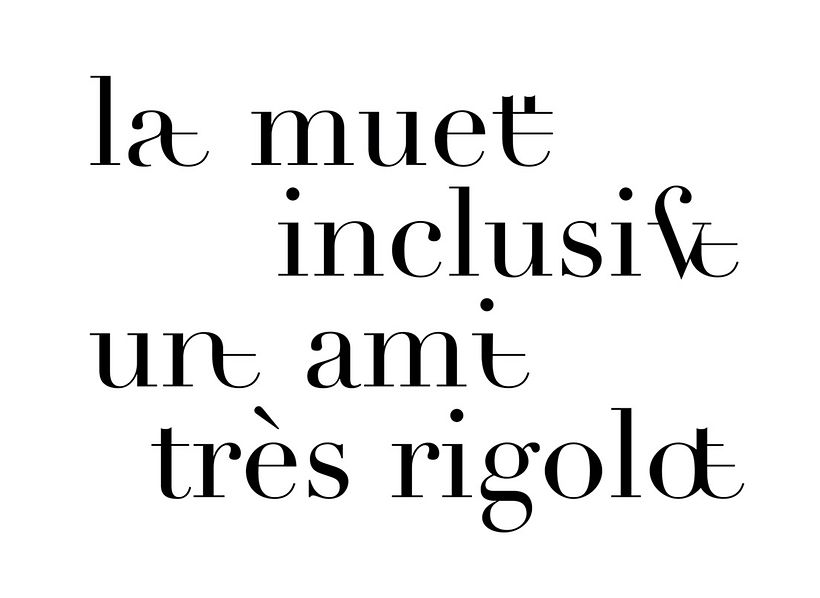
Siguiendo esta línea de diseño, hemos ideado tres símbolos nuevos que responden a tres necesidades de inclusión de género que consideramos fundamentales en la lengua española: el carácter “el/la”, el carácter “a/o” y el carácter “p/m”. Los tres símbolos buscan aunar el género masculino con el femenino de manera que se economice el lenguaje pero sin invisibilizar el género femenino, como en ocasiones ocurre cuando decimos “los padres”, cuando realmente nos estamos refiriendo a “el padre y la madre” o incluso a “las madres”.
El castellano es una lengua con una fuerte carga de género. Para los diseñadores es todo un reto tratar de aportar soluciones gráficas inclusivas a la par que estéticamente agradables, tratando de buscar alternativas más funcionales y serias que las usuales “x”, “@” y “e”. Esta es solamente una propuesta que hacemos desde nuestra agencia, una tipografía experimental que intenta dar respuesta a una necesidad gráfica y social cada vez más presente.
No podemos forzar la evolución del alfabeto de la noche a la mañana, ya que, al igual que la evolución de la lengua, es un proceso orgánico que debe darse de manera natural mediante su uso. Un buen ejemplo es el alfabeto Braille, que fue diseñado por un joven ciego, Louis Braille, ante la necesidad de hacer más funcional e intuitivo el sistema de Barbier, que es el que se utilizaba hasta el momento para enseñar a leer a las personas ciegas. El sistema de Barbier era ingenioso, partía de una buena idea: generar un sistema de escritura que permitiera a los soldados y oficiales franceses redactar y leer mensajes encriptados en la oscuridad y poder descifrarlos con los dedos. Sin embargo, Braille supo perfeccionar su diseño y lo hizo accesible y funcional para todo el mundo.
Igual que pasó con el alfabeto Braille, estamos convencidos de que con el tiempo y con la práctica irán surgiendo nuevas propuestas de sistemas de escritura universales, como esta tipografía inclusiva de género.
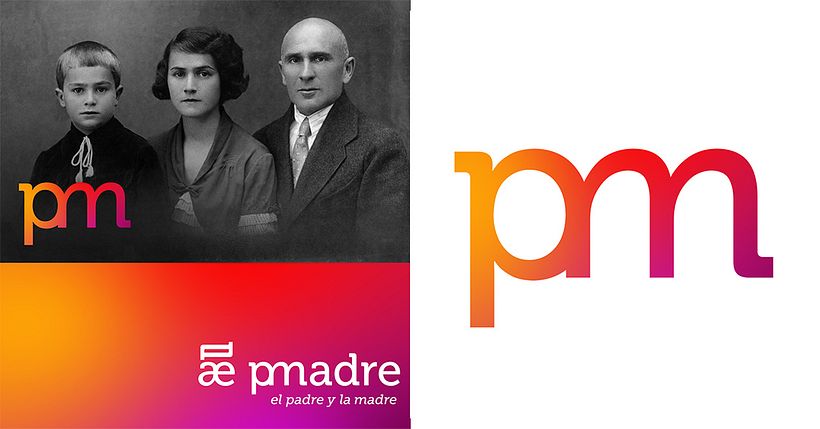
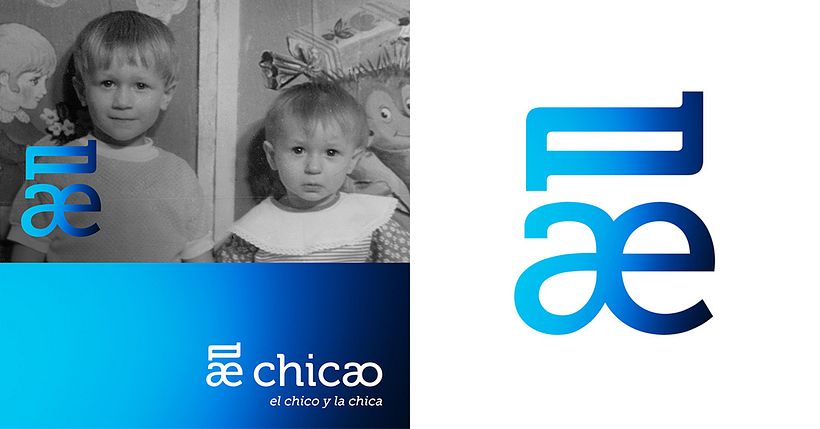
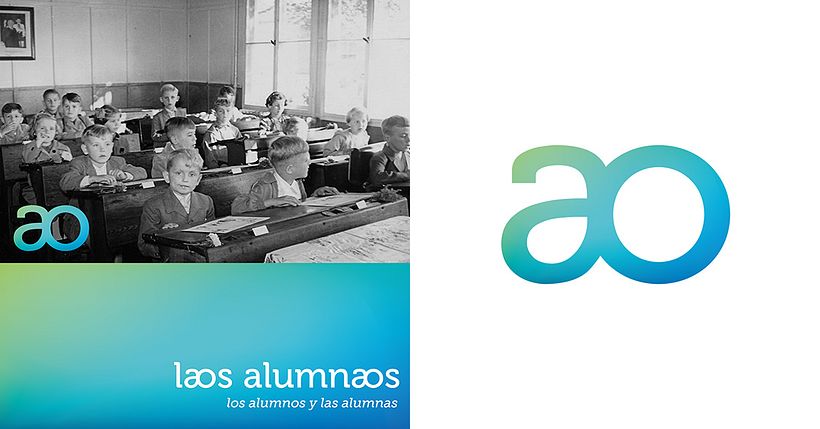
¿Qué os parece? ¿Creéis que es posible economizar el lenguaje y ser inclusivo al mismo tiempo? ¿Os parece que esta solución gráfica puede prosperar? ¿Cómo lo resolveríais vosotros? ¡Abrimos debate! 😉
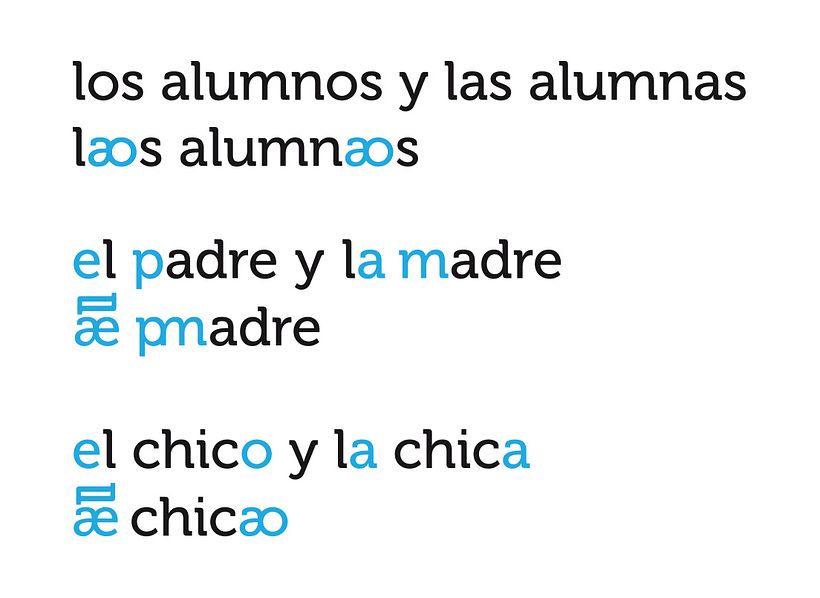
Tremendæ estupidæz
Es el colmo de lo ridiculo
El lenguaje inclusivo nace como reacción al machismo en el idioma, en el cual en la mayoria de los casos el genérico es masculino, pero eso no cambia nada, el inglés ni siquiera tiene género y hay machismo en la sociedad, igual o peor.
Este es el escenario en el que recibimos la propuesta desde la Agencia “CRECE” de incorporar, para avanzar en uso del lenguaje inclusivo y de economía el grafema “ao”. Es mas que aceptable la propuesta. Se enmarca en la línea de evolución del lenguaje con alfabetos mas amplios mas plurales y mas capaces de comunicar realidades emergentes. Bienvenida sea si con ella se consigue un idioma mas inclusivo y con esta realidad se mejora el lenguaje.